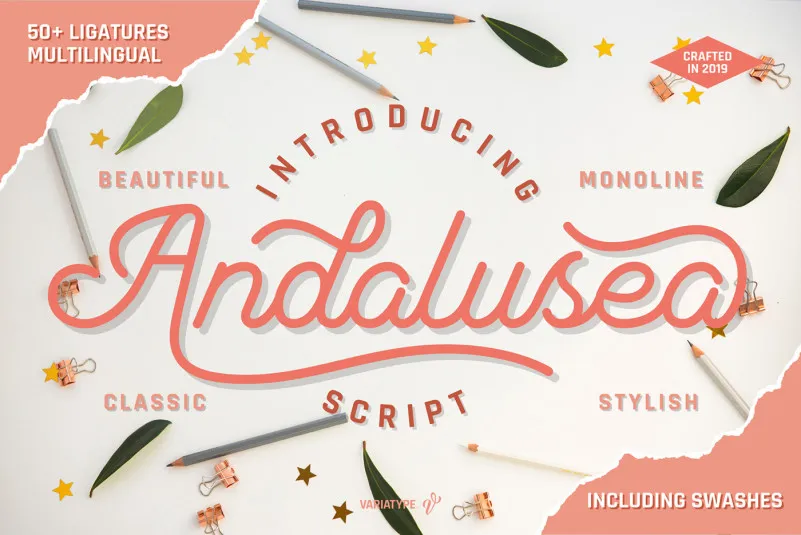
Andalusea Script Font – Download Grátis
A fonte ‘Andalusea Script Font’ é uma preciosidade para qualquer designer que busca adicionar um toque elegante a suas criações digitais. Desenvolvida pelo designer variatype, esta signature font traz os frutos do seu talento, apresentando linhas fluidas e curvas suaves que parecem fluir como o próprio texto ao ser escrito. Embora não haja detalhes exatos sobre características específicas da fonte em seu descrição original em inglês, a Andalusea Script é projetada para complementar textos de alta qualidade, desde editoriais até design gráfico. Suas linhas delicadas e equilibradas são ideais para criar um texto personalizado que destaca sua marca ou projeto, oferecendo uma maneira única de expressar suas ideias. Este recurso visual não só melhora a legibilidade como também torna o design mais atrativo, tornando-a perfeita tanto para projetos profissionais quanto para criações pessoais que exigem um toque único e sofisticado.
Designer: variatype